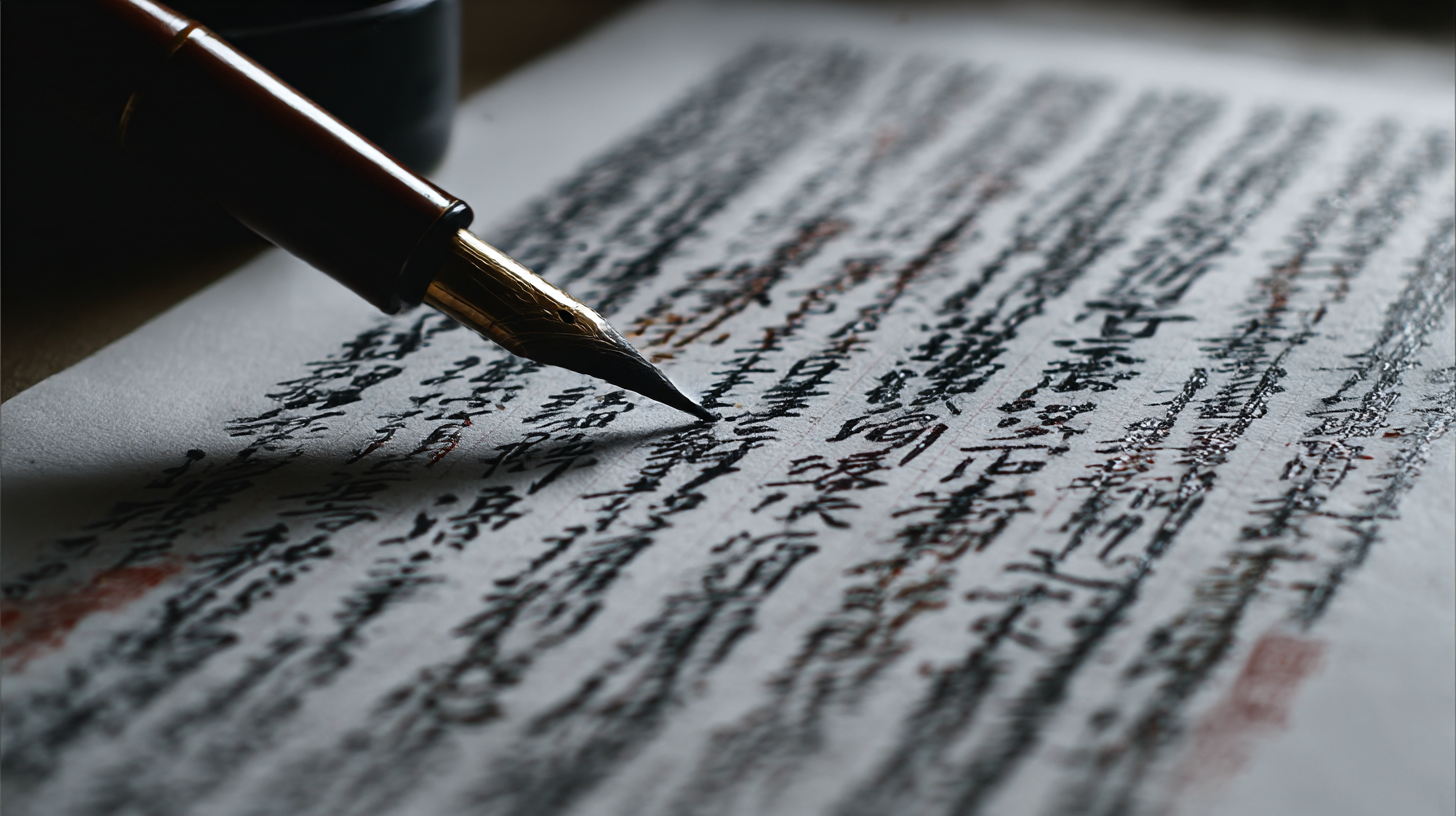
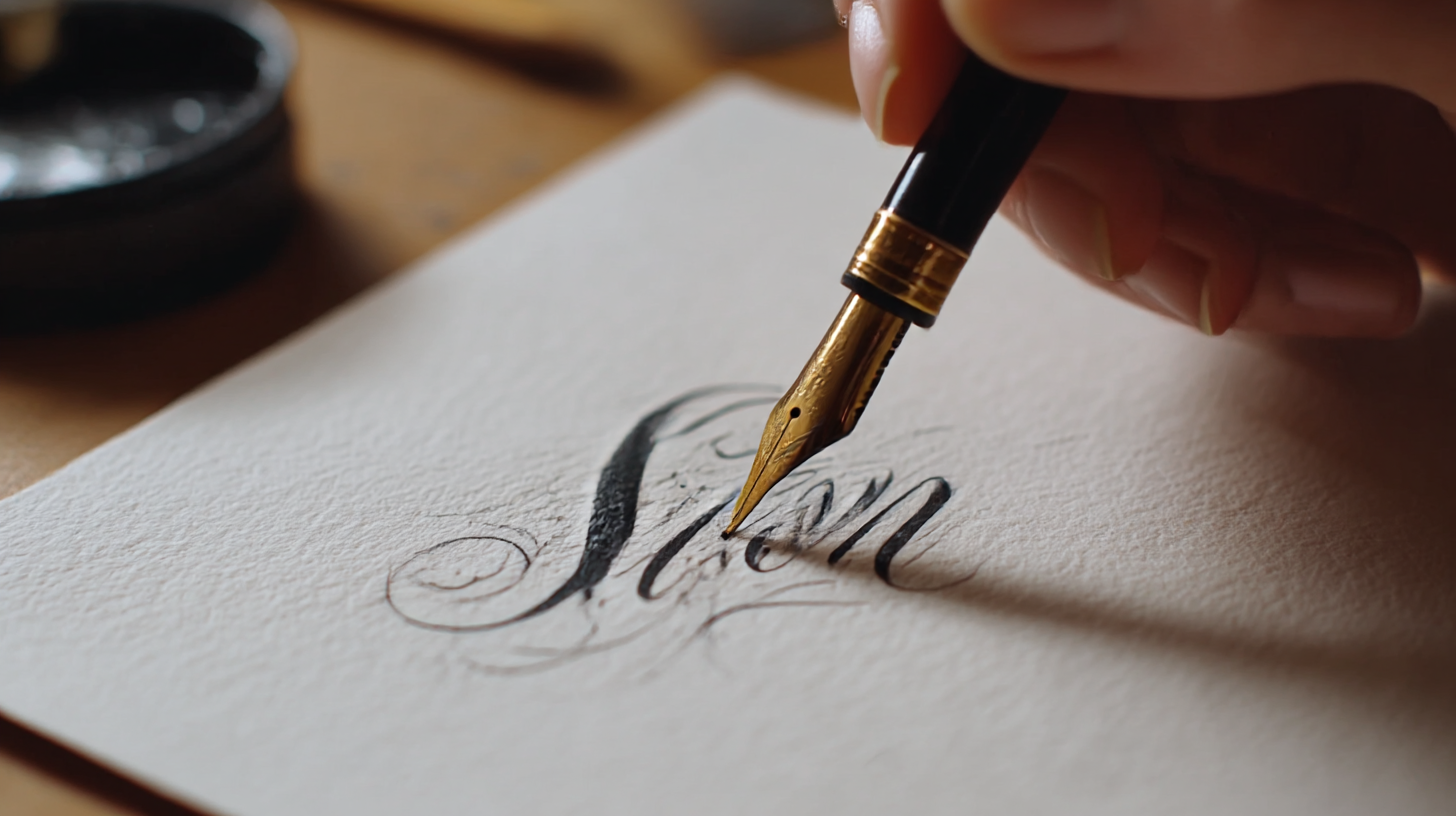
캘리그라피 독학, 가능한가요? 입문자용 가이드 캘리그라피는 손글씨의 예술이라고도 불려요. 단순한 글씨를 넘어서 감정을 담고, 분위기를 연출할 수 있는 매력이 있죠. 요즘엔 인스타그램, 유튜브, 블로그 등에서 멋진 캘리그라피 작품들이 자주 보이면서 입문하는 분들도 많아졌어요.
입문자들은 종종 '학원이나 수업 없이 과연 혼자 배울 수 있을까?'라는 고민을 하곤 하는데요. 결론부터 말하자면, 충분히 독학이 가능해요! 요즘은 다양한 온라인 자료와 도구들이 잘 마련돼 있어서 누구나 집에서도 시작할 수 있답니다. 그럼 지금부터 입문자도 쉽게 따라올 수 있도록 캘리그라피 독학 가이드를 소개할게요 😊
✍ 캘리그라피란 무엇일까?
캘리그라피(Calligraphy)는 '아름다운 글씨'라는 뜻의 그리스어 'Kallos(아름다움)'와 'Graphia(쓰기)'에서 유래했어요. 단순한 손글씨가 아니라 조형미를 갖춘 예술로 발전한 형태죠. 전통적인 의미에서는 붓이나 펜을 이용해 글자에 예술적인 느낌을 부여하는 작업이랍니다.
한국에서는 '손글씨'라는 말로 종종 혼용되지만, 정확히 말하면 캘리그라피는 글자를 꾸미는 표현 예술이에요. 감정을 담아 한 글자 한 글자 써 내려가는 그 행위 자체가 일종의 명상처럼 느껴질 수 있답니다. 그래서 요즘은 스트레스 해소용 취미로도 인기가 높아요.
과거에는 서예와 같은 전통적인 형태가 많았지만, 현재는 다양한 스타일로 진화했어요. 붓펜, 브러시펜, 마카 등 다양한 도구를 활용해 자유롭고 개성 넘치는 글씨를 연출할 수 있게 되었죠. 폰트처럼 기계적인 글씨가 아니라 손에서 직접 나오는 감성이 담긴 글자라 더 특별하답니다.
또한 캘리그라피는 인테리어 소품, 카드, 선물 포장, 플래너 꾸미기 등 실생활에서도 다양하게 활용돼요. 내가 쓴 글씨 하나로 소중한 사람에게 따뜻한 마음을 전할 수 있다는 점이 가장 큰 매력이죠. 그래서 입문자들도 하나둘씩 시작하게 되는 거예요.
🖋 캘리그라피와 손글씨 차이점
구분 손글씨 캘리그라피 정의 일상적인 글쓰기 예술적 표현의 글쓰기 도구 일반 펜, 연필 붓펜, 브러시펜 목적 정보 전달 감성 표현 형태 간결하고 규칙적 자유롭고 창의적 내가 생각했을 때 캘리그라피의 진짜 매력은 자신만의 손글씨를 통해 감정을 표현할 수 있다는 점이에요. 글씨에 기분이 담겨 있다는 게 정말 신기하거든요. 😊
🧠 왜 독학이 가능한 취미인가요?
캘리그라피가 독학으로 충분히 가능한 이유는 간단해요. 첫째, 시작에 필요한 비용이 적고, 둘째, 온라인 자료가 아주 풍부하다는 점이에요. 요즘은 유튜브, 블로그, 인스타그램 릴스 등에서 무료 강의부터 따라하기 영상까지 정말 다양하게 제공되고 있어서 누구나 쉽게 접근할 수 있어요.
또한 캘리그라피는 정답이 있는 학문이 아니라 감성과 표현 중심의 예술이기 때문에, 내 방식대로 연습하고 시도해보는 것이 매우 중요해요. 규칙보다는 개성과 창의성을 존중하는 분야라서 혼자 배우기에 더 잘 맞는 취미라고 볼 수 있죠.
학원을 다니면 단점도 있어요. 예를 들어 선생님의 스타일에 갇히거나, 내 속도에 맞춰 배우지 못하는 경우도 있거든요. 반면 독학은 나만의 속도와 스타일로 자유롭게 탐구할 수 있는 장점이 있어요. 언제 어디서든 펜만 들면 바로 시작할 수 있는 것도 큰 매력이에요!
무엇보다도 요즘은 입문자를 위한 캘리그라피 워크북, 가이드북, 연습용 PDF 등도 많이 나와 있어서, 온라인 커뮤니티나 카페에서 쉽게 구해서 연습할 수 있어요. 디지털 시대의 강력한 장점이죠 😊
📚 독학 시 활용 가능한 무료 플랫폼
플랫폼 특징 추천 활용법 유튜브 영상 강의와 실전 예시 기초 강의 시청 및 따라 쓰기 인스타그램 짧고 감각적인 콘텐츠 작품 참고 및 연습 블로그 글 중심의 설명과 후기 도구 사용법, 워크북 추천 온라인 카페 공유와 소통 작품 피드백 받기 혼자서도 충분히 실력을 키울 수 있는 환경이 잘 갖춰진 지금, 캘리그라피는 누구나 시작할 수 있는 최고의 힐링 취미가 되었어요. 다음은 어떤 도구들이 필요한지 알려줄게요! 🖌
🖌 입문자를 위한 기본 도구 소개
캘리그라피를 처음 시작할 때 가장 궁금한 게 바로 "어떤 도구가 필요한가요?"일 거예요. 다행히 처음엔 고가의 장비나 전문용품 없이도 얼마든지 시작할 수 있답니다. 기본 도구만 잘 갖추면 충분히 멋진 글씨를 써볼 수 있어요. 지금부터 꼭 필요한 입문자용 준비물을 하나씩 알려줄게요!
첫 번째로 필요한 건 바로 '붓펜'이에요. 붓펜은 캘리그라피 도구 중 가장 대중적이고 사용이 간편한 펜이에요. 펜촉이 부드러워서 두께 조절이 쉽고, 잉크가 고르게 나와서 연습하기에 딱 좋아요. 시중에선 모나미, 사쿠라, 펜텔, 쿠레타케 등의 브랜드 제품이 인기가 많아요.
두 번째는 연습용 노트! 아무 노트나 써도 되지만, 종이가 너무 얇으면 잉크가 번질 수 있으니 100g 이상의 두께를 추천해요. 아니면 캘리그라피 전용 워크북이나 가이드 라인이 있는 연습용 PDF를 인쇄해서 써보는 것도 좋아요. 글씨의 구조를 익히는 데 도움이 되거든요.
세 번째는 ‘지우개와 연필’이에요. "어? 캘리그라피에 연필도 쓰나요?" 하실 수 있는데요, 기본 구조나 자간(글자 간격)을 연습할 땐 연필로 가이드라인을 그리는 게 정말 중요해요. 나중에 지우개로 지우면 깔끔한 작품이 완성돼요!
🧰 캘리그라피 입문 도구 리스트
도구 추천 이유 활용 팁 붓펜 유연한 필기감, 굵기 조절 가능 기본 획 연습에 적합 브러시펜 컬러 표현 가능 작품 제작 시 활용 연습노트 글씨 간격, 구성 훈련용 PDF 인쇄도 가능 연필 & 지우개 가이드라인 작성 미리 구도 설계 후 사용 도구를 선택할 때는 너무 비싸거나 어려운 걸 고르기보다는, 내 손에 잘 맞는 걸 찾는 게 중요해요. 인터넷 후기나 체험 리뷰를 참고하면서 고르면 실패 확률도 줄어들겠죠? 😄 다음은 실전 연습법과 연습 팁을 알려줄게요!
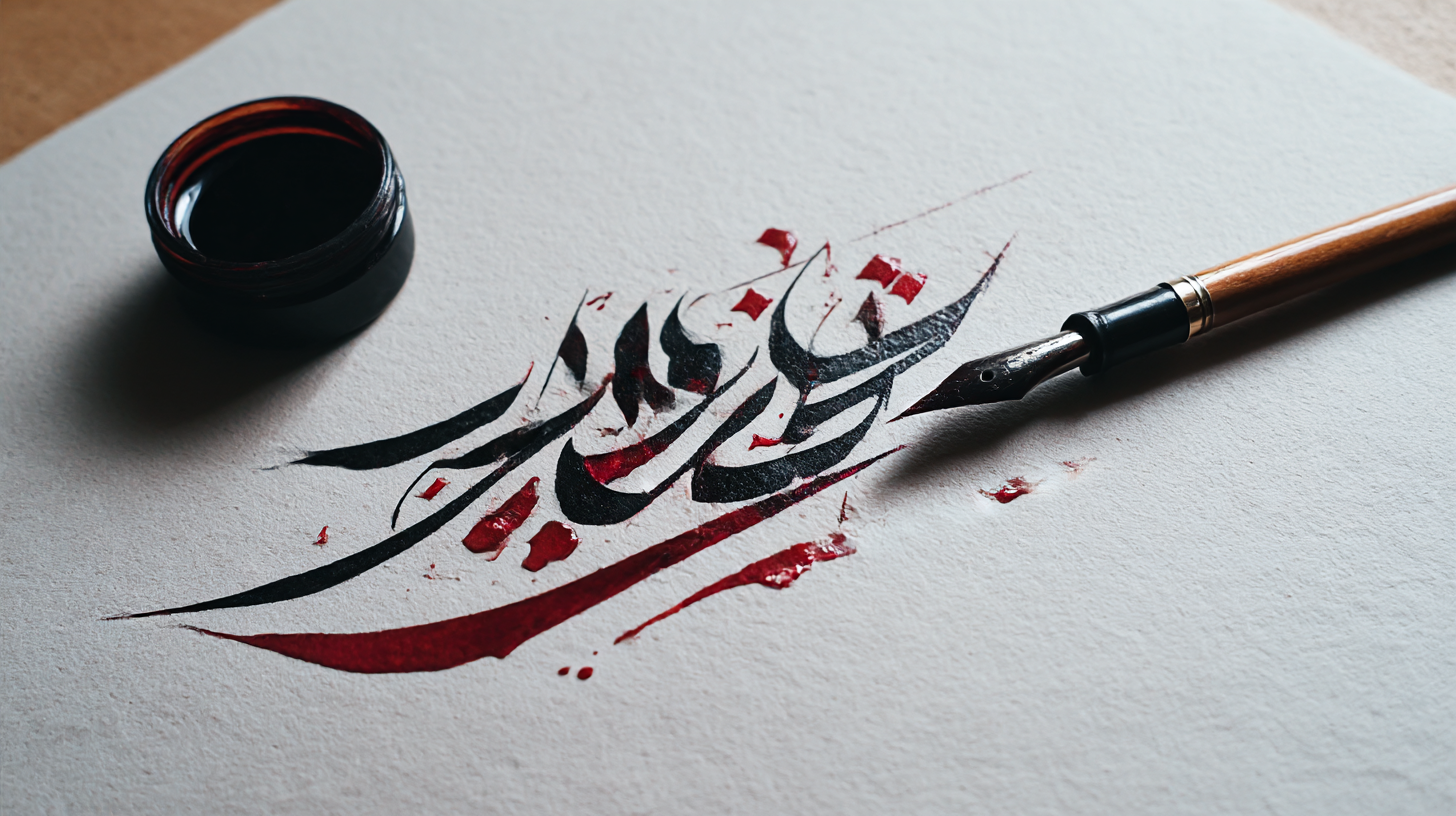
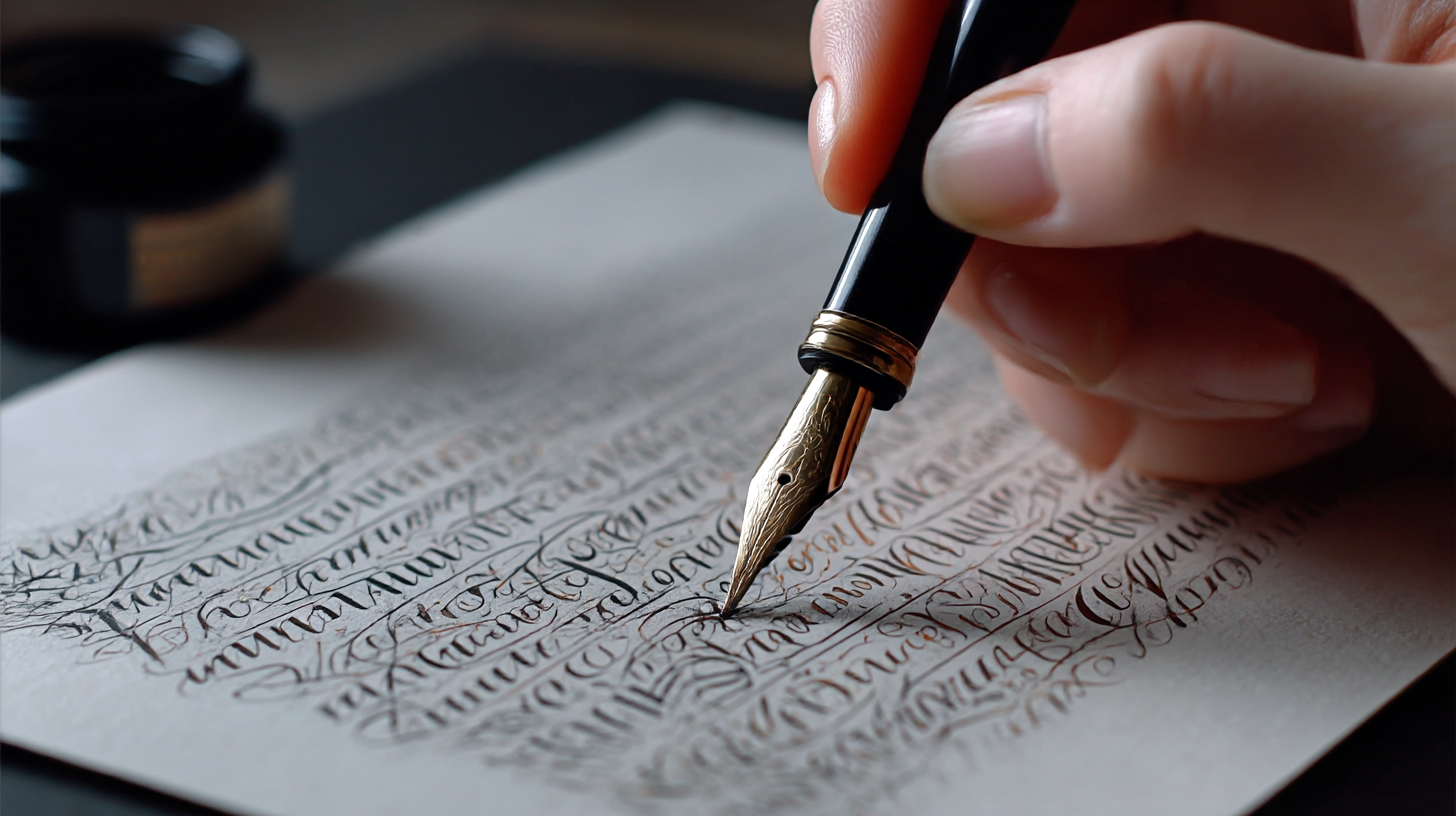
입문자를 위한 기본 도구 소개 ✏ 기초 연습 방법과 팁
도구를 준비했다면 이제 본격적으로 연습을 시작할 차례예요. 초보자에게 가장 중요한 건 ‘기본 획 연습’이에요. 단어를 쓰기 전에 ‘점, 선, 곡선, 눌렀다 떼기’ 같은 기본 동작을 반복하는 게 좋아요. 이는 글씨의 안정감과 조형미를 잡는 데 큰 도움이 돼요.
처음엔 알파벳이나 한글 자모 단위로 연습하는 게 좋아요. ‘ㄱ, ㄴ, ㄷ’부터 ‘가, 나, 다’ 순서로 진행하면서 획의 연결과 자간을 익히면 돼요. 연습할 때 너무 빠르게 쓰기보다는 천천히, 선의 흐름을 느끼며 써보는 게 포인트예요. 손목과 팔을 유연하게 움직이며 종이 위에서 리듬감을 만들어보세요.
연습할 때 자주 쓰는 문구를 정해서 반복하는 것도 좋은 방법이에요. 예를 들어 "오늘도 빛나는 너에게", "감사합니다", "행복하자" 같은 간단하고 긍정적인 말들을 매일 반복하다 보면 자연스럽게 필력도 늘고, 문장 구도도 익숙해져요. 그리고 매일 하나씩 짧은 문구를 작품처럼 써보는 것도 재미있답니다!
또한 내 글씨를 스마트폰으로 촬영해서 피드백해보는 습관도 중요해요. 내가 어떤 부분에서 비뚤어졌는지, 글자의 크기가 균형을 이루는지 체크할 수 있거든요. 눈으로만 보는 것보다 객관적인 시선으로 내 글씨를 보는 게 정말 큰 도움이 돼요!
🧠 캘리그라피 연습 루틴 예시
시간 연습 내용 팁 10분 기본 획 5가지 반복 선 굵기 조절 연습 10분 자음/모음 반복 쓰기 모양 균형 확인 10분 짧은 문장 구성 다양한 레이아웃 시도 10분 내 글씨 촬영 및 피드백 비교해서 발전 확인 무조건 오래 연습한다고 실력이 늘진 않아요. 대신 짧게라도 꾸준히 매일 하는 것이 훨씬 효과적이에요. ‘매일 20분’만 실천해도 2~3주면 눈에 띄게 달라지는 걸 느낄 수 있어요. 다음은 다양한 스타일에 대해 알아볼게요! 🖍
🎨 다양한 캘리그라피 스타일 비교
캘리그라피에도 여러 가지 스타일이 있어요. 각 스타일마다 느낌과 쓰임새가 다르기 때문에, 입문자라면 다양한 스타일을 접해보면서 자신에게 잘 맞는 방향을 찾아가는 게 중요해요. 정형화된 글씨보다는 감정과 분위기를 담는 게 핵심이라, 글씨체마다 개성이 뚜렷하답니다.
가장 기본적인 스타일은 '붓글씨형 캘리그라피'예요. 전통 서예와 유사한 느낌을 주며, 붓펜을 활용해 굵기 조절과 흐름의 자연스러움을 중시해요. 붓으로 쓴 듯한 부드러운 곡선과 강약 조절이 매력적이죠. 감성적인 문구나 명언을 쓸 때 많이 사용돼요.
두 번째는 '모던 캘리그라피' 스타일이에요. 요즘 SNS에서 자주 보이는 감성적인 손글씨 스타일로, 기존의 전통적인 틀을 깨고 보다 자유로운 형태로 구성돼요. 브러시펜을 많이 사용하며, 디자인 요소를 가미한 형태로 카페 메뉴판이나 인스타 문구 등에 잘 어울려요.
세 번째는 '타이포 캘리그라피'로, 다양한 굵기와 폰트 느낌을 믹스한 스타일이에요. 한 문장 안에서 굵기와 높낮이를 일부러 다르게 써서 리듬감 있게 표현해요. 제목이나 포스터 디자인에서 시선을 끌기에 좋아요. 다만 균형 잡는 감각이 필요하니 조금 연습이 필요해요.
🖍 캘리그라피 스타일별 특징 비교표
스타일 주요 특징 사용 도구 어울리는 용도 붓글씨형 전통적인 강약 조절 강조 붓펜, 수묵 붓 명언, 인사말 모던 캘리그라피 감성적이고 자유로운 구성 브러시펜, 마카 SNS 콘텐츠, 엽서 타이포 스타일 굵기와 배열을 강조 멀티펜, 마카펜 포스터, 제목 디자인 이런 다양한 스타일 중에서 하나를 선택해도 좋고, 여러 가지를 섞어서 자신만의 스타일을 만들어도 멋져요. 완벽한 글씨보다 중요한 건 ‘느낌 있는 표현’이라는 거, 꼭 기억해주세요 😊 다음은 혼자서 꾸준히 연습하는 루틴을 소개할게요!
📅 혼자서 꾸준히 연습하는 루틴
캘리그라피를 독학으로 꾸준히 연습하려면 ‘습관화’가 가장 중요해요. 처음엔 매일 5분이라도 손에 펜을 쥐고 종이를 만지는 루틴을 만드는 게 좋아요. 규칙적인 연습은 감각을 잃지 않게 해주고, 발전 속도도 눈에 띄게 빨라진답니다.
가장 쉬운 방법은 ‘캘린더 루틴’을 만드는 거예요. 하루 하나씩 문장을 정해 쓰고, 날짜별로 어떤 문구를 쓸지 미리 계획해두면 동기부여가 되기도 해요. 예를 들어 1일엔 “잘하고 있어”, 2일엔 “오늘도 감사해”처럼 매일 다르게 연습하면 지루하지 않고 재밌게 이어갈 수 있어요.
A3. 하루 15~20분만 꾸준히 연습해도 2~3주 후면 확연한 차이를 느낄 수 있어요. 중요한 건 매일 ‘조금씩’이라도 하는 거예요.
Q4. 어떤 도구로 시작하면 좋을까요?
A4. 붓펜과 연습노트만 있으면 시작할 수 있어요. 쿠레타케, 사쿠라 등의 붓펜 브랜드가 입문자들에게 인기가 많아요.
Q5. 캘리그라피로 돈을 벌 수도 있나요?
A5. 네, SNS에서 팔로워를 모은 후 엽서 판매, 디자인 의뢰, 클래스 운영 등 다양한 수익 모델도 가능해요!
Q6. 디지털 캘리그라피도 독학이 가능할까요?
A6. 아이패드와 애플펜슬, 프로크리에이트 앱만 있으면 디지털로도 독학 가능해요. 유튜브 강의도 많아서 진입장벽이 낮아요.
Q7. 손이 떨려서 글씨가 안 예쁜데 어떡하죠?
A7. 처음엔 누구나 떨려요. 천천히 손목을 고정하고 호흡을 조절하면서 쓰면 점점 안정감이 생겨요. 연습할수록 좋아져요!
Q8. 혼자 하다가 슬럼프가 오면 어떻게 하나요?
A8. 잠깐 쉬어도 괜찮아요. 그동안 써왔던 글씨들을 다시 꺼내보거나, 다른 사람의 작품을 감상하면서 새로운 영감을 얻어보세요 ✨